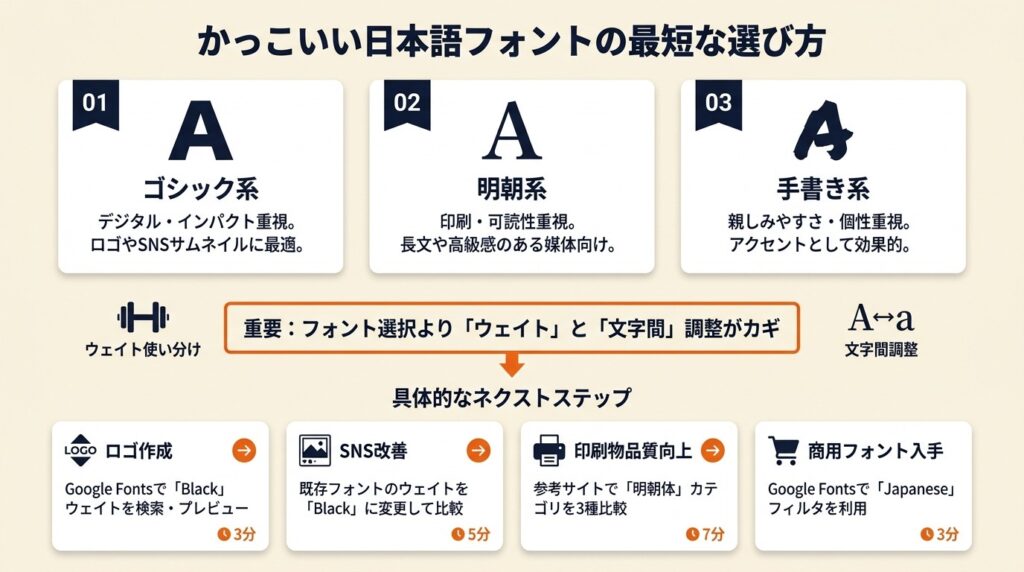
かっこいい日本語フォントを探すとき、ひらがな・漢字が揃わない、商用利用の可否が不明、という壁に当たる方は多い。本記事ではデザイン現場で実際に使える無料・商用可のかっこいい日本語フォント15種を用途別に解説する。
この記事でわかること
ゴシック・明朝・手書きの3系統でフォントを絞り込む方法
無料・商用可フォント15種を用途別に即選択できる分類
同じフォントでもウェイト調整だけで仕上がりが変わる理由
この記事の結論
かっこいい日本語フォントは「ゴシック系・明朝系・手書き系」の3系統に分類して選ぶと、用途とのミスマッチを防げる。無料かつ商用利用可のフォントは2025年時点で100種類以上存在しており、Google FontsやAdobe Fonts経由で安全に入手できる。ロゴ・サムネイル・印刷物それぞれに最適な系統が異なるため、本記事の分類と診断フローを活用して1本目のフォントを今日中に決めてほしい。
今日やるべき1つ
Google Fontsで「Noto Sans JP」を検索し、ウェイト「Bold」を選択してサンプルテキストに自分のロゴ文言を入力する(3分)。
かっこいい日本語フォントは3系統で選ぶ
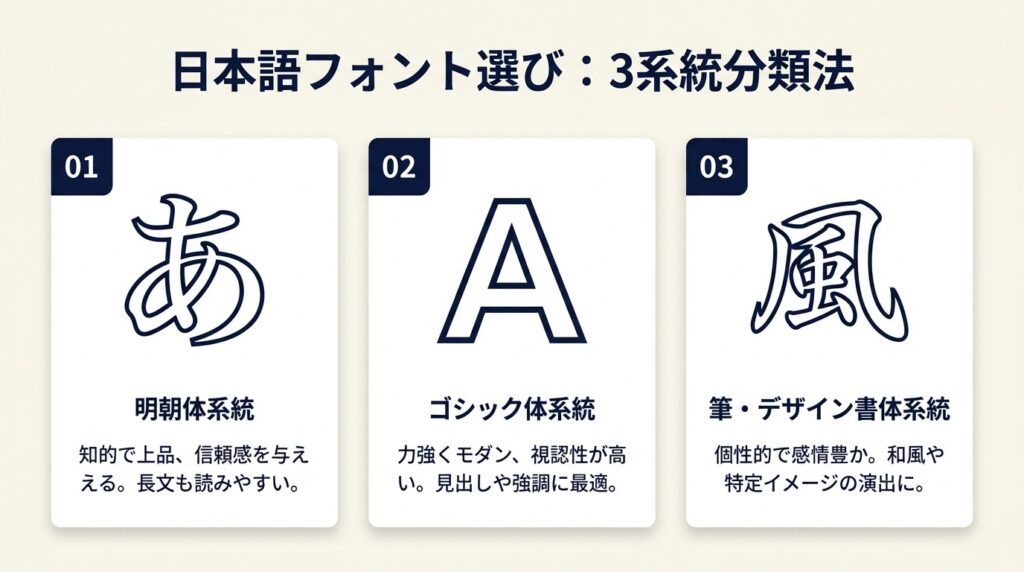
数百種類あるフォントを闇雲に比較するから決められない。まず3系統に分類すると、選択肢が一気に絞られる。
ゴシック系は力強さとモダンさを両立
ゴシック系フォントは文字の縦横の線幅が均一で、直線的な印象が強く出るのが特徴だ。かっこいい印象を最も直接的に演出できる系統であり、YouTubeサムネイルやロゴで多用されている。代表的なフォントとして「Noto Sans JP」「源ノ角ゴシック JP」が挙げられ、どちらもGoogle FontsやAdobe Fontsから無料で入手できる。ウェイト(太さ)を「Heavy」や「Black」に設定するだけで、同じフォントでも印象が大きく変わる。まずはウェイト違いを3段階で比較してほしい。
ゴシック系は視認性が高い分、使いすぎると単調になる。見出しのみに絞って使うと、本文テキストとのコントラストでよりかっこよく見える。
明朝系はシャープさと格式感を演出
明朝系は横線が細く縦線が太い、和風・格調系のかっこよさを出せる系統だ。ゴシック系とは異なり、「凛とした」「静的な強さ」を表現したいブランドロゴや書籍タイトルに向いている。「源ノ明朝」や「はんなり明朝」は商用利用可で全文字対応しており、印刷物でも品質が安定している。
ゴシック系と明朝系を組み合わせる手法はデザイン業界で広く用いられており、タイトルにゴシック、本文に明朝を当てると読みやすさとインパクトを同時に確保できる。日本語フォント無料おすすめ12選でも、ゴシック体と明朝体の組み合わせ方は実務での活用例として詳しく紹介されている。
手書き・デザイン系は個性と差別化に直結
手書き系・デザイン系フォントは、他のサイトやコンテンツとの差別化に最も効くジャンルだ。ただし、ひらがな・カタカナ・漢字の全文字が収録されていないものも多く、使用前に必ず文字セットを確認してほしい。「藍原筆文字凜華」「京華老宋体」のようなレトロモダン系は2025年のデザイントレンドと合致しており、SNSコンテンツや商品パッケージで視覚的インパクトを出しやすい。手書き系は乱用すると読みにくさが生じるため、1デザインにつき1書体の使用を原則にしてほしい。
よくある質問
Q: ゴシック体と明朝体はどちらがかっこいいですか?
A: 用途によって判断が変わる。力強く現代的なかっこよさにはゴシック体、格式や静的な強さを表現したい場合は明朝体が適している。2系統を組み合わせる方法が最も汎用性が高い。
無料商用可フォントは15種で網羅
プロのデザイナーが業務で使用するレベルのフォントが無料で公開されている。Canvaの日本語フォントまとめでも紹介されているように、2025年時点では厳選された無料フォントだけで大半のデザイン案件をカバーできる。
ゴシック系おすすめ5種
「Noto Sans JP」はGoogleが開発した全文字対応のゴシック体で、ウェイトが9段階あり、ロゴから本文まで1書体で使いまわせる。Webフォントとしても使いやすく、現在最も広く使われている日本語フォントの一つだ。「源ノ角ゴシック JP」(Source Han Sans JP)はAdobeとGoogleが共同開発したオープンソースフォントで、Adobe Fonts経由で無料利用できる。「ゴツデラゴシック」は太めのウェイトが特徴で、YouTubeサムネイルや告知バナーのタイトルに使うと視認性の向上が期待できる。「飴鞭ゴシック」は細身でモダンなゴシック体で、ファッション・コスメ系のブランドロゴによく合う。「M PLUS 1p」はクリーンで読みやすいゴシック体で、プレゼン資料やWebサイト見出しへの汎用性が高い。
明朝系おすすめ3種
「源ノ明朝」(Source Han Serif)は源ノ角ゴシックと同じくAdobeとGoogleが開発した明朝体で、全角・半角・記号を網羅している。印刷物にも対応しており、商業出版レベルのクオリティを無料で利用できる。「はんなり明朝」は柔らかさの中に凛とした印象があり、Webサイトのキャッチコピーや名刺デザインに向いている。「刻明朝」はエレガントで引き締まった印象が強く、高級感を演出したい商品パッケージや映像テロップに使われている。
手書き・デザイン系おすすめ7種
「藍原筆文字凜華」は書道家によるデザインで、日本語の全文字セットをカバーしており、他の手書きフォントと比較して可読性が高い。「京華老宋体」はレトロモダンなデザインで、昭和・レトロ感とスタイリッシュさを同時に出せる。「ISEKAI FONT」はゲーム・アニメ系コンテンツに特化したフォントで、YouTubeサムネイルやゲーム内タイトルで使用実績が多数ある。「おてんばゴシック」はインパクトが強く扱いやすい、初めて試すのに適したフォントだ。「Kiwi Maru」はCanvaでも使用できる手書き風フォントで、柔らかさの中にかっこよさを感じさせる。Adobe Fontsで利用可能な「雫花ゴシック」は現代的でありながら和の美しさを持つ。「たぬき油性マジック」はPOP系の手書き風フォントで、SNSコンテンツや告知物に使うと親しみやすさとインパクトを両立できる。
よくある質問
Q: Canvaで使える日本語かっこいいフォントはどれですか?
A: Canvaでは「Noto Sans JP」「Kiwi Maru」「M PLUS 1p」などが標準で使用できる。Canvaの日本語フォント一覧ではデザイナー選定の日本語フォントが確認でき、プレビュー機能で即確認できる。
用途別フォントを3分で診断
おすすめフォント一覧を見てもどれを選べばいいか分からない場合は、用途から逆算すると決断が早まる。次の診断フローで自分のケースを特定してほしい。
Q1: 主な使用目的はデジタル(Web・SNS・動画)ですか?それとも印刷物(名刺・ポスター・パッケージ)ですか?
デジタル用途の場合はQ2へ進む。印刷用途の場合はQ3へ進む。
Q2(デジタル用途): インパクト重視ですか?それとも読みやすさ重視ですか?
インパクト重視の場合はResult A(ゴシック系Heavy/Black)、読みやすさ重視の場合はResult B(ゴシック系Regular〜Medium)。
Q3(印刷用途): 高級感・格調を出したいですか?それともポップな印象にしたいですか?
高級感・格調を求めるならResult C(明朝系または細身ゴシック)、ポップ・親しみやすさを求めるならResult D(手書き・デザイン系)。**
Result A: YouTubeサムネイル・ロゴ向け「ゴツデラゴシック」または「源ノ角ゴシック JP Black」を使用してほしい。テキストのウェイトをBlack以上に設定し、文字の周囲に2〜4pxの白縁(アウトライン)を加えると視認性がさらに高まる。
Result B: WebサイトやSNS投稿の見出し向け「Noto Sans JP Bold」または「M PLUS 1p Bold」を選択してほしい。行間を1.6〜1.8に設定することで読みやすさとスタイリッシュさを両立できる。
Result C: 名刺・高級ブランドロゴ・書籍向け「源ノ明朝 Medium」または「刻明朝」を使用してほしい。余白(マージン)を文字サイズの1.5倍以上確保することで、格調ある印象が際立つ。
Result D: チラシ・POP・SNSコンテンツ向け**「藍原筆文字凜華」または「ISEKAI FONT」から始めてほしい。手書き系は1デザインにつき1書体に限定し、サブテキストには読みやすいゴシック体を組み合わせるとまとまりが出る。
よくある質問
Q: 1つのデザインに何種類のフォントを使っていいですか?
A: 原則2種類以内。見出し用と本文用の2役に絞ると、デザインの統一感が保たれる。3種類以上使用すると視覚的なノイズが増え、かっこよさより散漫な印象が勝る。
Q: ひらがな・カタカナ・漢字すべてに対応したかっこいいフォントはありますか?
A: 全文字対応フォントとして「Noto Sans JP」「源ノ角ゴシック JP」「源ノ明朝」の3種が代表的だ。これらはJIS第1・第2水準漢字を網羅しており、日常使用する文字でフォントが欠けることはほとんどない。sankoufont.comでウェイト別にプレビューして確認できる。
Q: YouTubeサムネイルにかっこいい日本語フォントを使う際の注意点は?
A: サムネイルはスマートフォンで小さく表示されるため、細いウェイト(Regular・Light)は視認性が低下する。Bold以上のウェイトを使用し、文字色と背景色のコントラスト比を4.5:1以上に設定してほしい。白文字に黒縁取り2〜4pxを加えると、どの背景色でも読めるサムネイルになる。